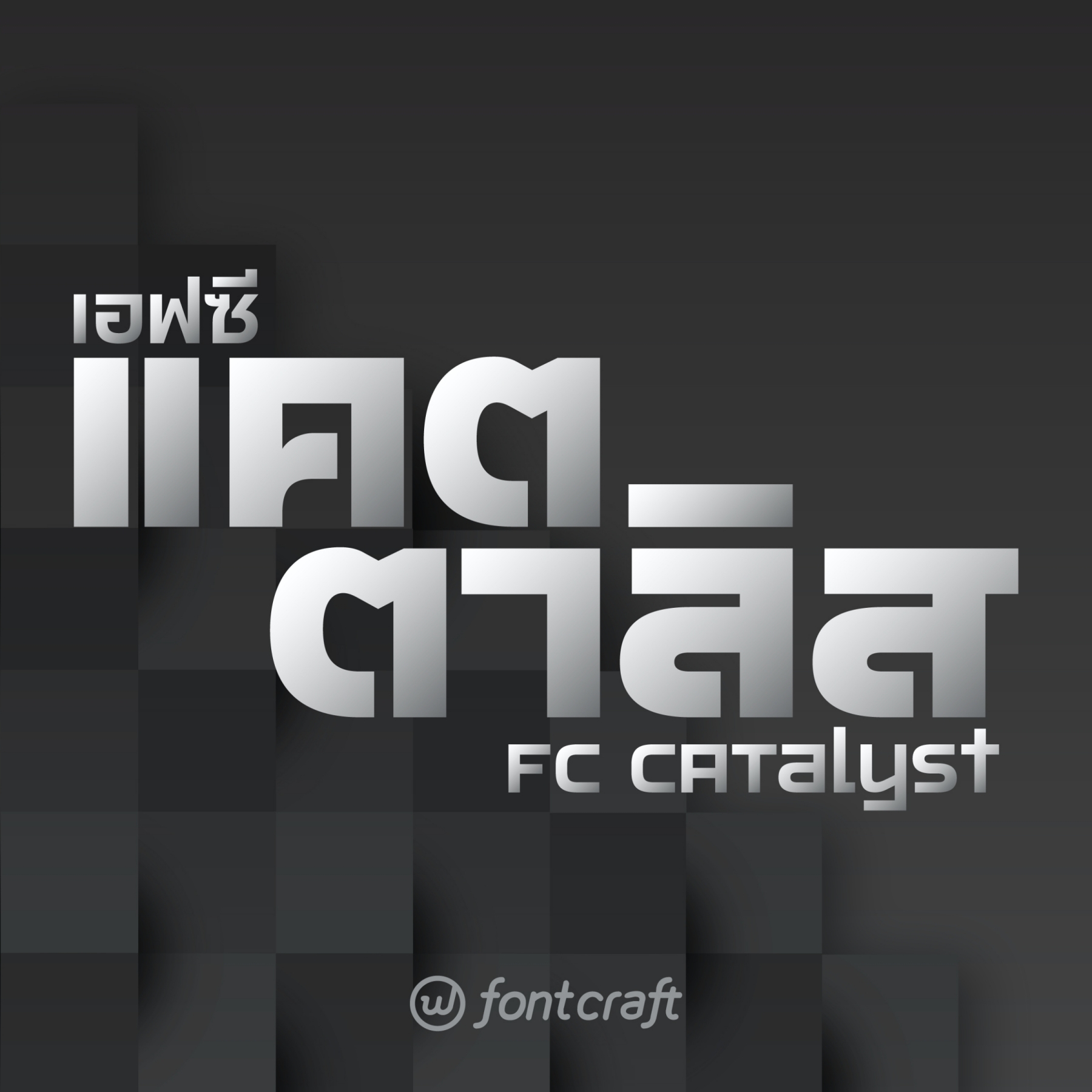
เอฟซี แคตตาลิส (FC Catalyst)
ฟอนต์เอฟซี แคตตาลิส (FC Catalyst)
อยากลองทำแบบเรียบๆ แต่มีอะไรซ่อนอยู่แบบนี้มานานนน ได้เวลาปล่อยของครับ
ฟอนต์เอฟซี แคตตาลิส (FC Catalyst)
ความลงตัวของเส้นตรงและเส้นโค้ง เกิดเป็นความสวยงามแสนเรียบง่าย
เส้นตรงและเส้นโค้งคือสารตั้งต้นของตัวอักษร ผ่านการแปรสภาพโดยฟอนต์เอฟซี แคตตาลิส เกิดเป็นผลลัพธ์ของกลุ่มคำที่มีเอกลักษณ์สัมผัสสายตา
โดยความสูงของตัวอักษรเท่ากันทั้งภาษาอังกฤษ ภาษาไทย ตัวเลข สัญลักษณ์ ทำให้สามารถผสมตัวพิมพ์ใหญ่และตัวพิมพ์เล็กในคำเดียวกันได้
เท่แบบเท่มากๆ ครับตัวนี้